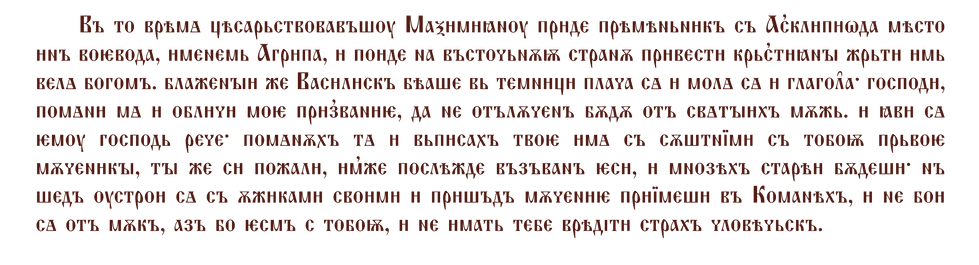
Шрифт Кирилловский/DXKirillovskiy
Гарнитура: DXKirillovskiy
(в составе шрифтов DXKirillovskiy, DXKirillovskiyOlden)
Тип: Акцидентный
Начертание: Regular
"Шрифт Шафарик", созданный по заказу чешского учёного-слависта Павла Йосефа Шафарика в 30-ые годы XIX века.
"Шафарик, шрифт, созданный чешским ученым Шафариком в 30-х годах прошлого века. Образцом послужил ему почерк Остромирова евангелия, но от уменьшения и сжатия буквы потеряли монументальный характер XI в. Этот характер сохранили только заглавные буквы «шафарика», но и они слишком широки и крупны для передачи целых текстов. Заглавный шафарик незаменим для передачи памятников эпиграфики: славяно-русской и византийской, — монументальных надписей на камне, металле, дереве и пр. При этом греческое и («ипсилон») передается славянским заглавным Y («червь»). По своему виду «шафарик» (как и его прототип — Остромирово евангелие) очень походит на греческий искусственный устав X в. и позднейших веков и содержит все нужные для него буквы."
Цифровая версия шрифта разработана в 2016 году. Образцами послужили оттиски шрифта из Каталога словолитни О.О.Гербек и Каталога образцов шрифтов Императорской Академии наук, 1852, 1870 гг.
Гарнитура состоит из двух начертаний: обычного(Reguar) и исторического(Olden).
Историческое начертание соответствует образцам шрифта из Каталогов, однако в составе набора знаков присутствуют цифры для строчных и прописных букв, современные начертания некоторых букв в качестве альтернативных знаков. Для удобства набора исторических текстов, основной набор акцентов размещен на местах расположения латинского алфавита, для строчных кириллических знаков на месте строчных латинских знаков, для прописных на месте латинских прописных.
В состав Обычного начертания входит стандартный набр латинских знаков, современный кириллический алфавит, два набора цифр, альтернативные знаки, исторические кириллические знаки, акценты, титла, специальные исторические знаки.